デザイン筆文字では唯一無二の存在! 印章店がデジタルフォントで新境地を切り拓いた、白舟書体
FONTPLUSでご利用いただけるフォントメーカー14社(2021年4月現在)をご紹介するコーナー。今回は、毛筆書体の流れを踏襲し、デザイン筆文字で新境地を切り拓いた「白舟書体」を紹介します。
FONTPLUSが誕生したのは今から10年前の2011年7月。その年の11月に毛筆書体の専門フォントメーカーの白舟書体とWebフォント配信で提携しました。
では最初に、白舟書体の代表的なフォントで、居酒屋のメニューによくある「串焼き盛り合わせ」を表現してみましょう。
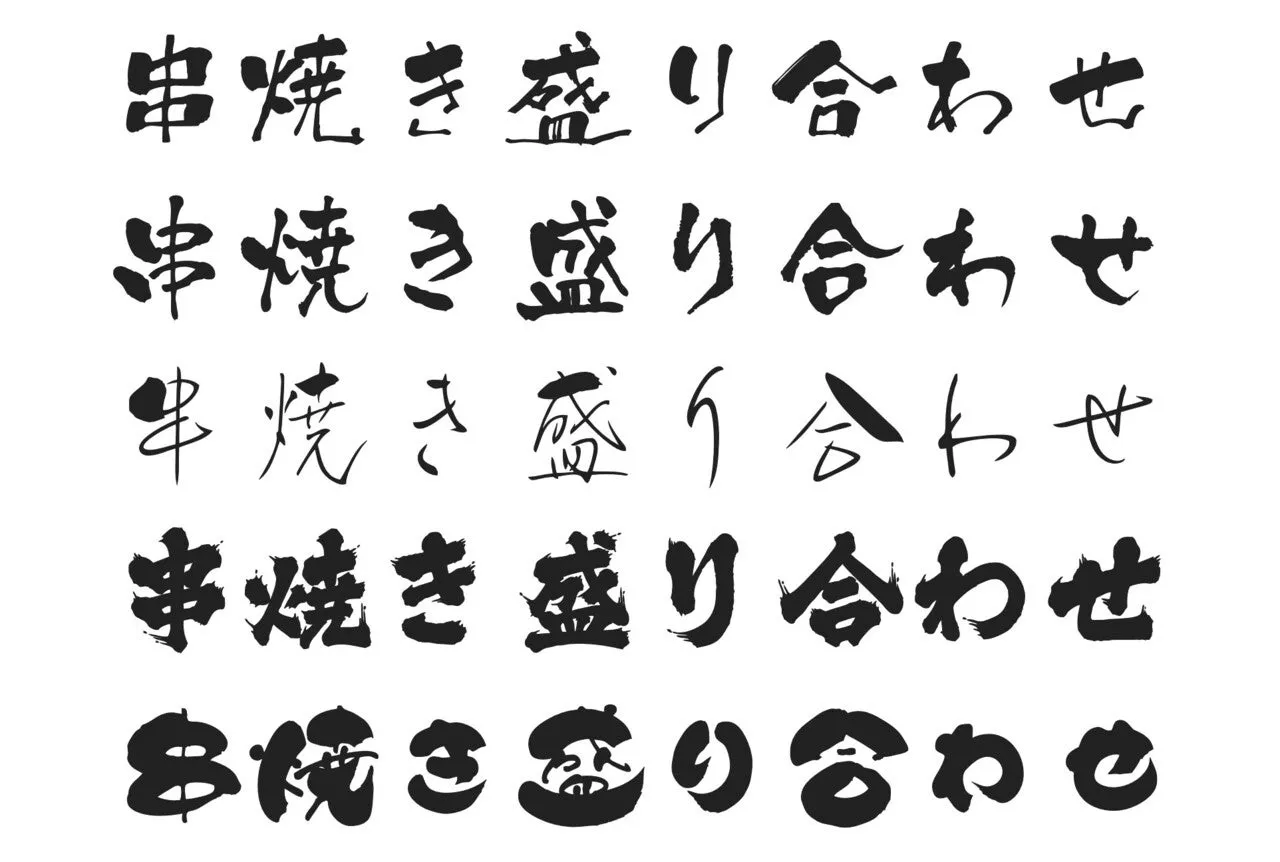
居酒屋メニューでは、明朝体やゴシック体、丸ゴシック体よりも、毛筆書体が似合いますよね。思わず、オーダーしたくなります。ここで使用したフォントは、上から「鯨海酔侯」「京円」「桜花」「大髭」「まめ福」です。居酒屋メニューで鉄板系フォントです。これらの書体は、テレビのテロップや日本酒や焼酎のラベルでもよく目にします。次のサンプルは、上から「白舟篆書」「白舟篆古印」「白舟小篆」「忍者」「万葉古印ラージ」です。
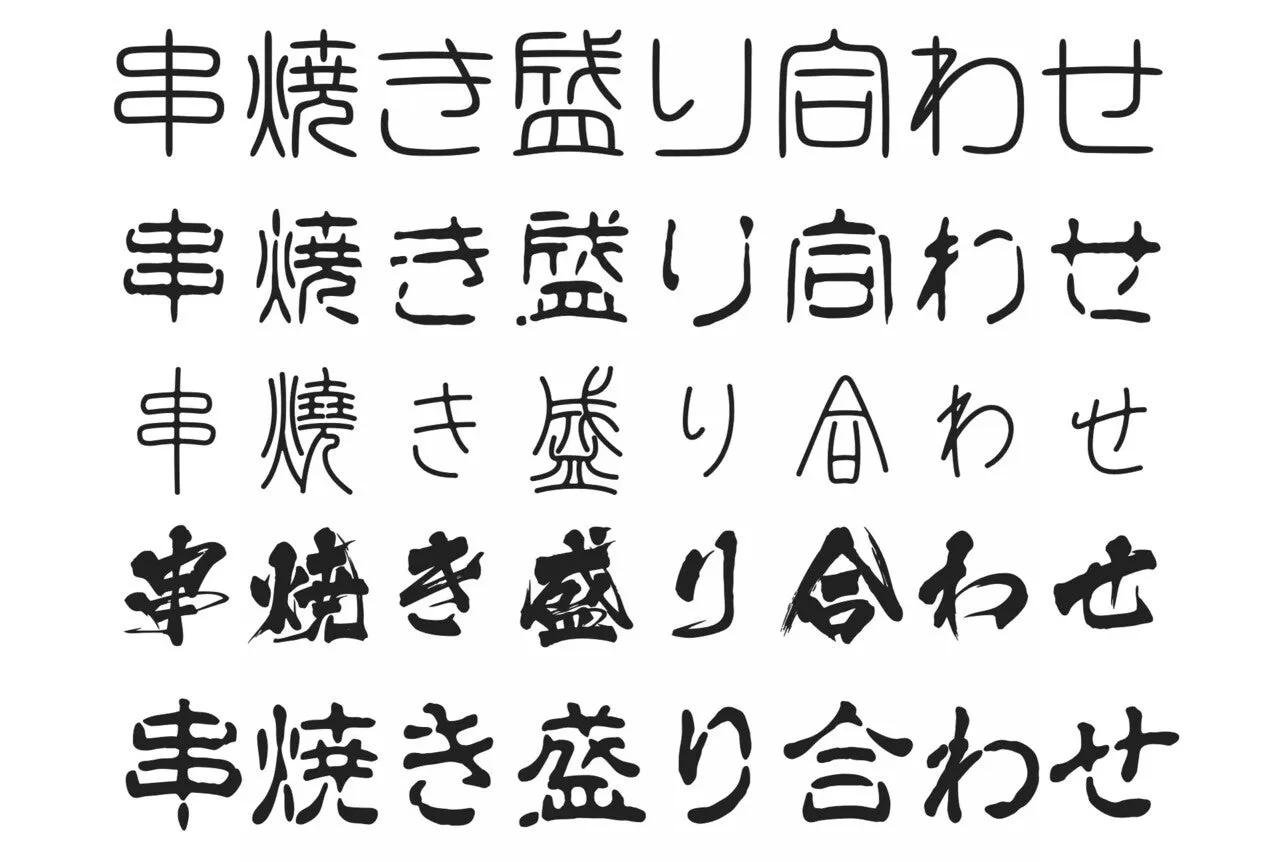
毛筆書体というと、楷書、行書、草書といった伝統的なスタンダードな書体をイメージする人が多いと思います。一方で「デザイン筆文字」という新境地のジャンルのフォントが、2002年頃から印刷物、チラシなどで多く使われるようになりました。それが「白舟書体」なのです。昨今、これら筆文字がウェブサイトでも使われるようになってきました。
白舟書体は1996年創業。毛筆書体のデジタルフォントメーカーとして有名ですが、会社のルーツがとても興味深いので紹介します。
白舟書体の前身は、1934年創業の「丸岡白舟印舗」という印章店です。丸岡勝(まさる)氏が兵庫県の小さな町で印鑑屋を始めたそうです。当時は、印鑑に手で文字を逆さまに書いて、それをご自身で1本1本掘って制作していたとのこと。分業ではなく、ひとりで作業を完結していたそうです。
印鑑書体として、印相体(いんそうたい)、篆書体(てんしょたい)、古印体(こいんたい)、隷書体(れいしょたい)など多くの原字を手書きで制作していたということなのです。すごい……。
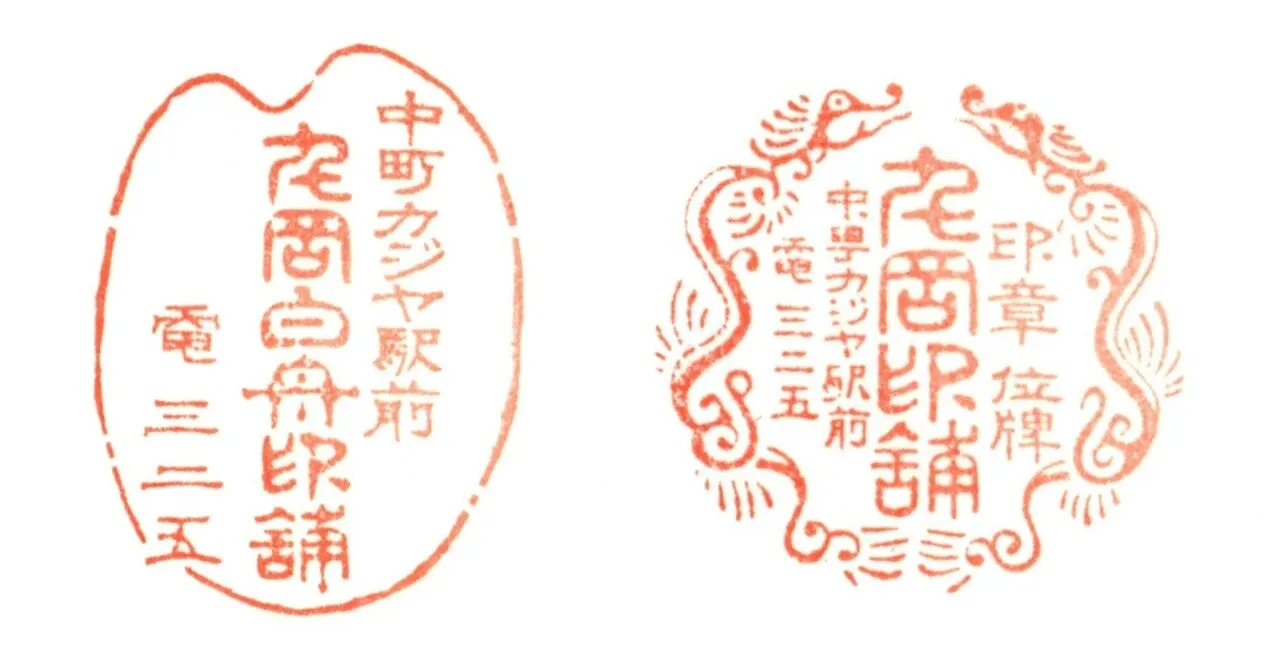
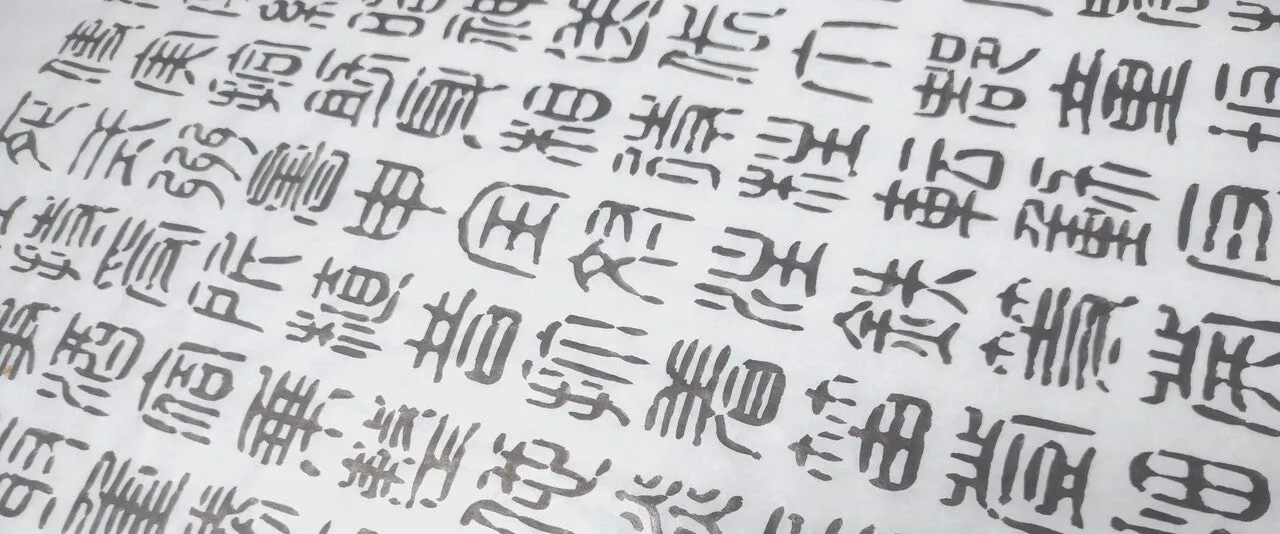
ところで、古印体って書体は怖い文字だと思っている人が多いですよね。でも、古印体は、本来、印鑑の文字なので、怖い文字ではありません。下記の古印体の一文字を赤い丸枠で囲って赤字で表現すると、印鑑にしか見えませんよね。
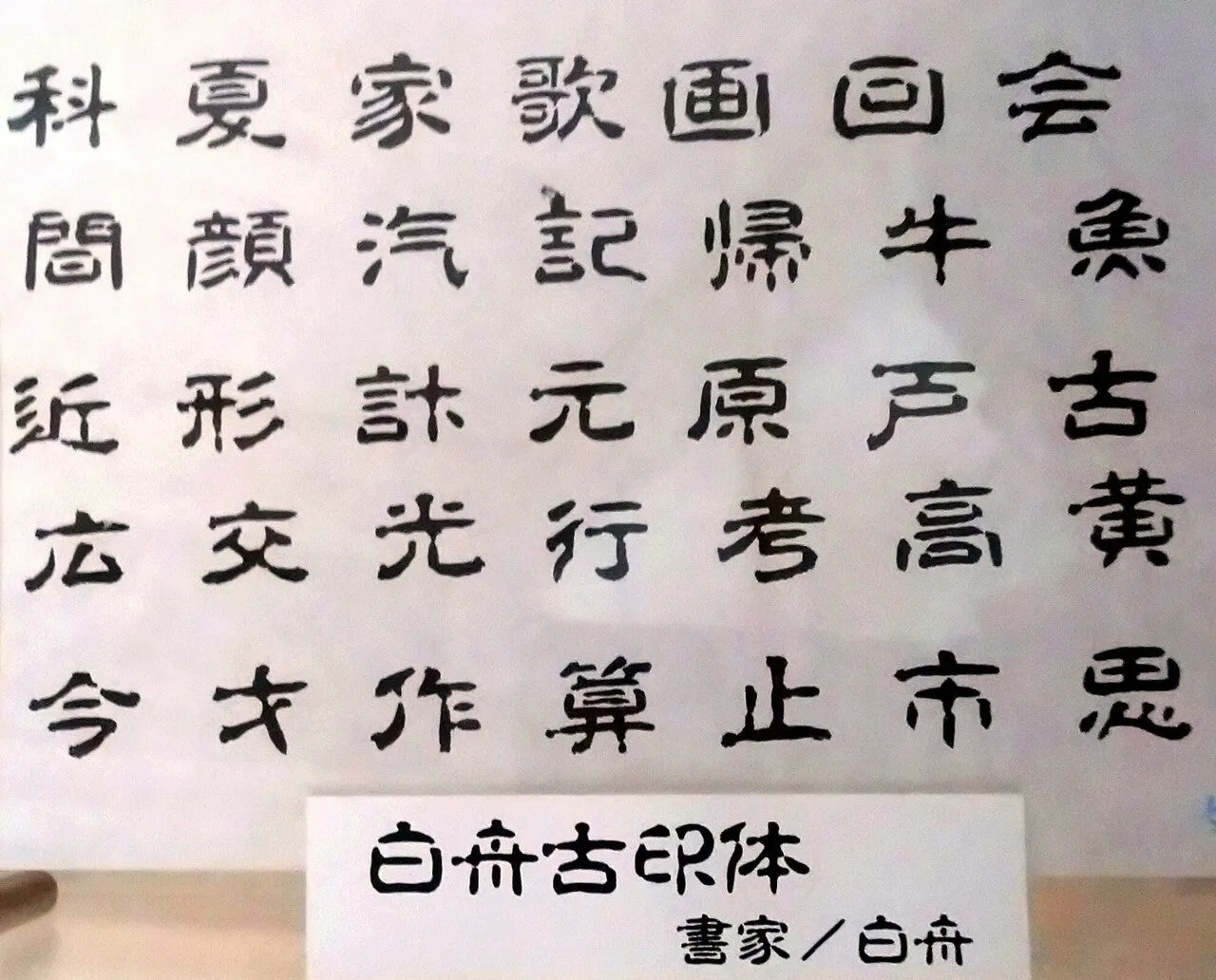
1990年代に入ると、印鑑の文字を手書きで書いて、手彫りする職人が少なくなりました。そこで、丸岡白舟印舗の跡継ぎであった丸岡雅憲(まさのり)氏は、それらの原字をスキャンしてデジタル化したそうです。すると、周りの印章店から、そのフォントを使いたいという声が多く寄せられたそうです。1996年、「白舟書体」のブランド名でデジタルフォントの販売を開始。1999年にはシヤチハタ社への書体提供も開始し、現在では、ほとんどの印章店で白舟書体が使用されるようになりました。
そして、2002年に白舟書体として人気の「鯨海酔侯」「京円」「侍」が「デザイン筆文字シリーズ」としてリリース。これらのフォントは、居酒屋メニュー、お酒の広告、テレビテロップなどで重宝され、あっという間に人気書体になりました。
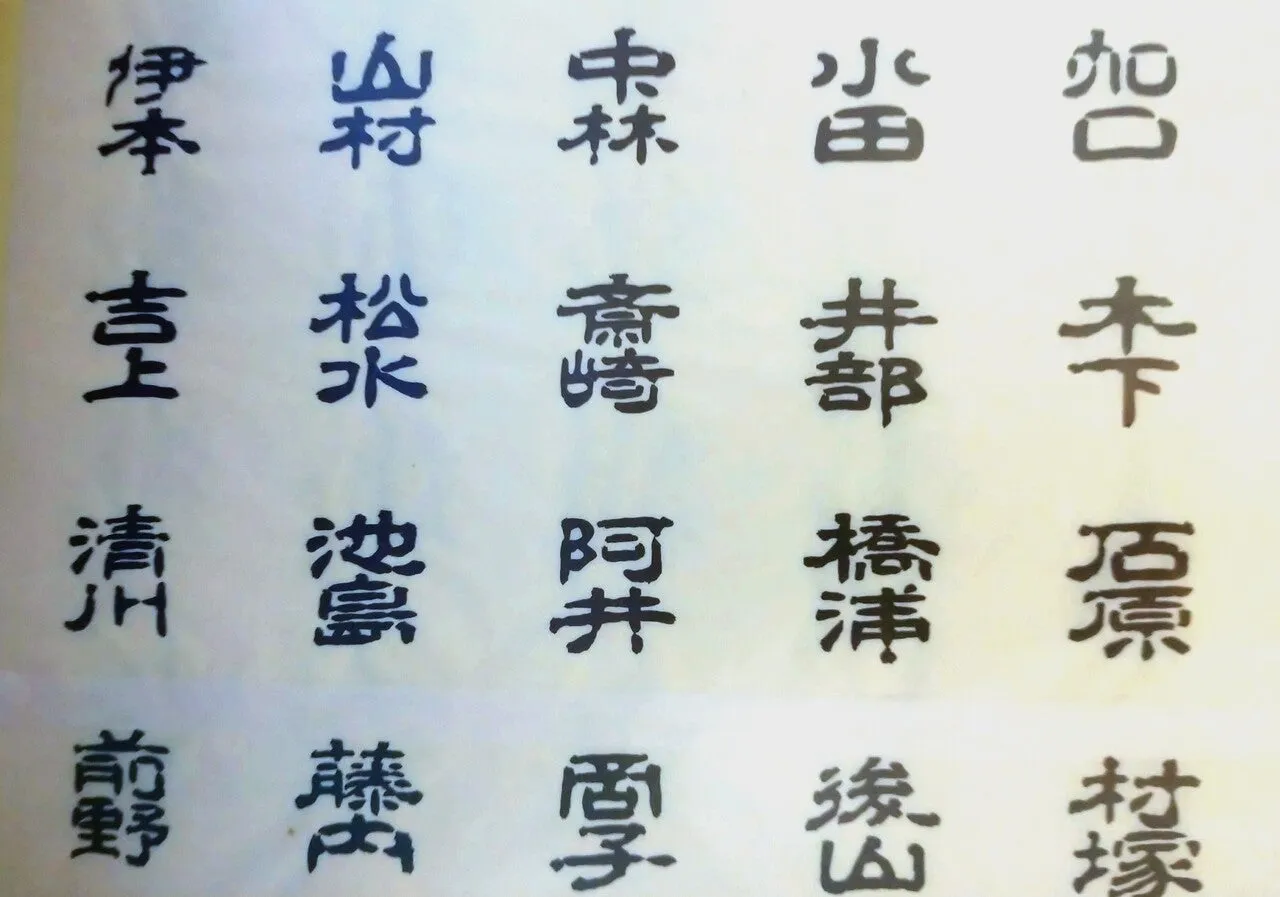
居酒屋メニューの鉄板書体と言えば、「鯨海酔侯」です。この書体が生まれたきっかけは、白舟書体の会社の近くにある居酒屋の筆文字を書いている方との出会いがあったからだそうです。そして、「京円」と「侍」は、近所の印章店の筆職人が書いた文字をベースに制作したとのことです。つまり、直接お会いして一緒に作れる距離の範囲で筆職人を発掘してきて、デジタルフォント化するビジネスモデルなのです。それを考えついたのが丸岡雅憲氏だったのです。
そして、このビジネスモデルの発展形も生み出します。今度は、筆文字を書くセンスのある筆職人を発掘して、育成・プロデュースするビジネスモデルです。その代表書体が「隼風」「大髭」「まめ吉」「忍者」とのこと。どのフォントも、特徴があり、インパクトのある素敵な書体ですよね。これら書体の原字を書いた女性は、当初、白舟書体にパートで入社して、出荷や書体制作の補助の仕事をしていたそうです。筆で文字を書いた経験があるとのことで、雅憲氏が監修しながら、書体プロデュースしたところ、人気書体を続々と誕生させたのです。
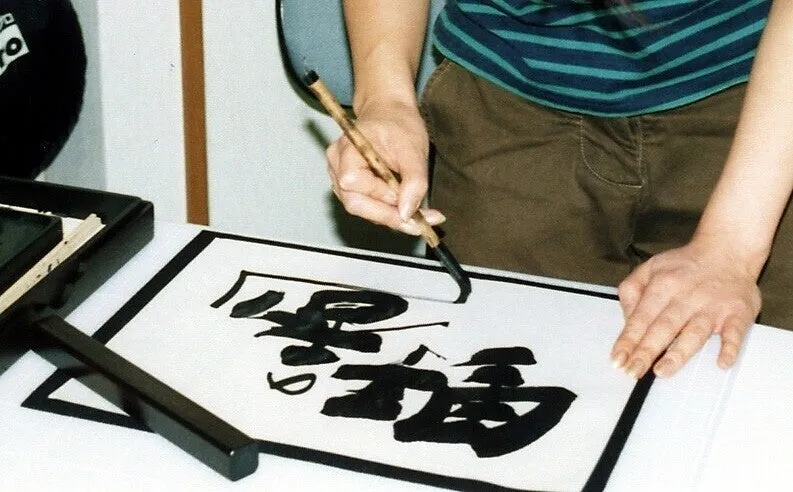
印章店をルーツにもつフォントメーカーにしかできない毛筆書体の文化を継承しつつ、独自のビジネスモデルを構築したことに感動しました。
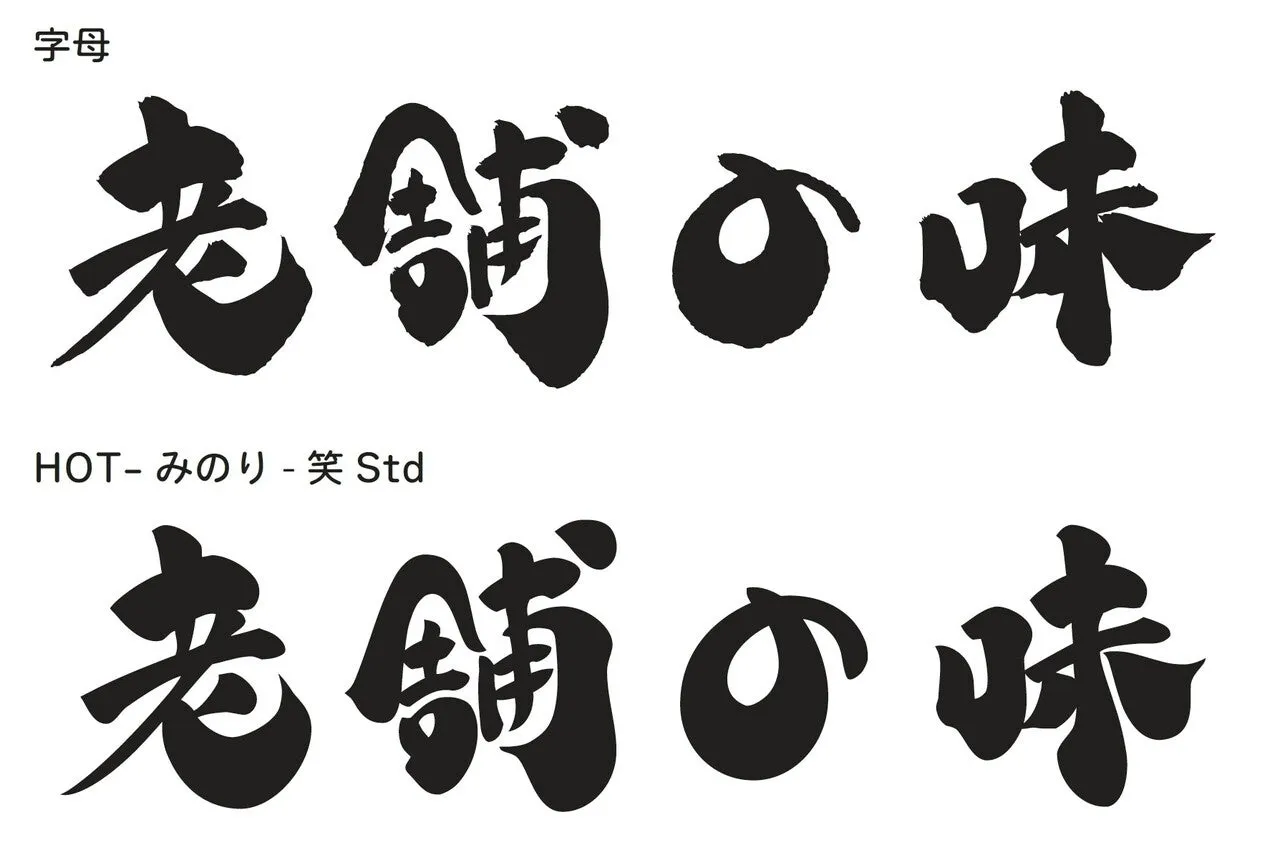
パソコン用フォントとして、白舟書体が2020年4月にリリースした「みのり」という書体があります。このフォント、今までありそうで無かったテイストの筆文字だと思いませんか。筆文字なのに、アウトラインがツルツルしています。袋文字にも対応しやすそうです。FONTPLUSでWebフォントとしてご利用いただけます。